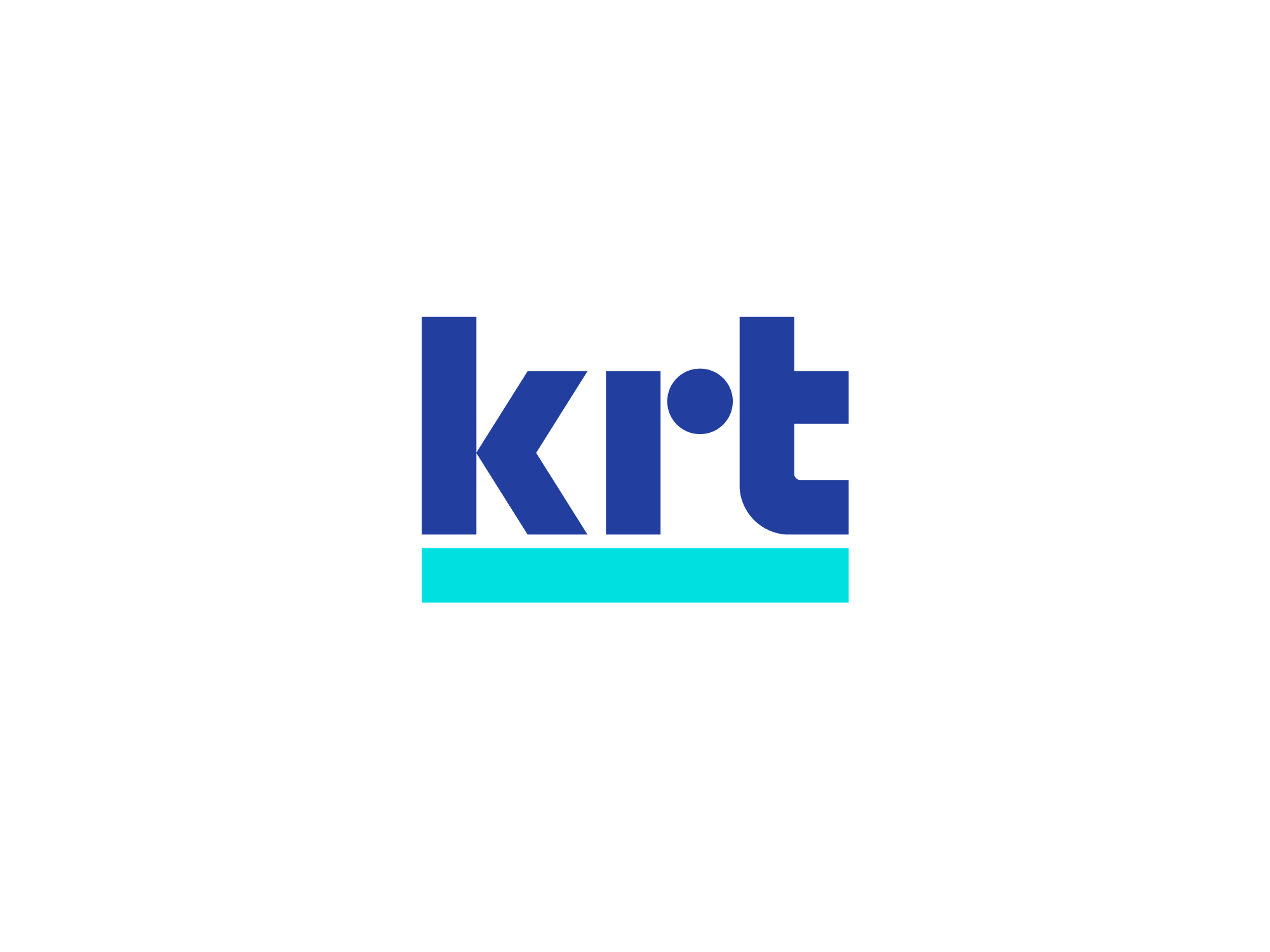
KRT
Logo pre tradičnú slovenskú sieť kúpeľňových štúdií a predajcu tovaru pre kompletné zariadenie kúpeľní KRT Pekné kúpeľne.
Logo je vyskladané z jednoduchých geometrických ťahov, diagonál a zahnutí a evokuje tak dizajnovú priamočiarosť a modulárnosť. Napriek abstraktnosti jednotlivých tvarov si logo zachováva dobrú čitateľnosť. Formálna čistota loga je podporená výrazným podčiarknutím.